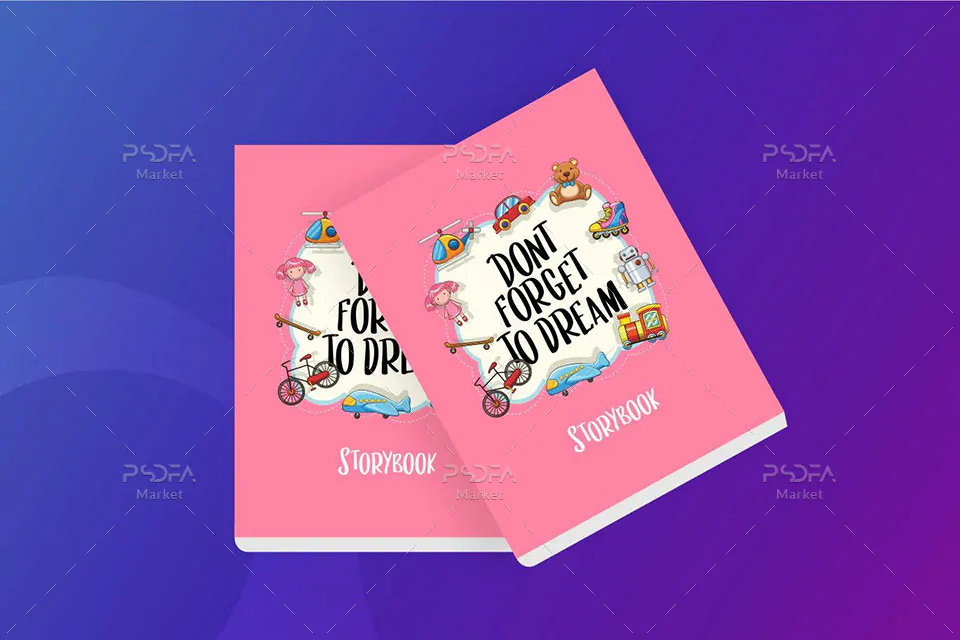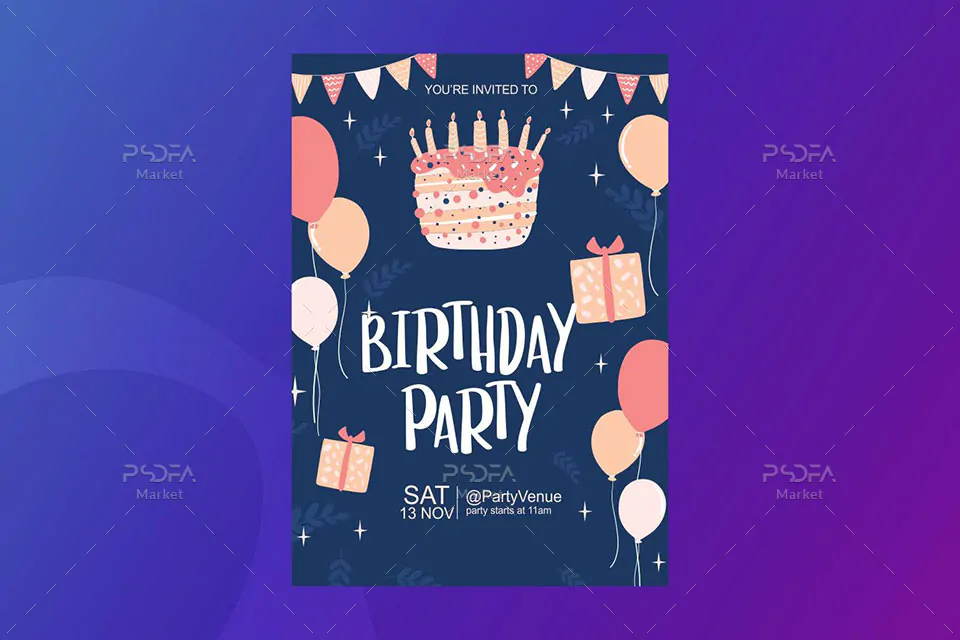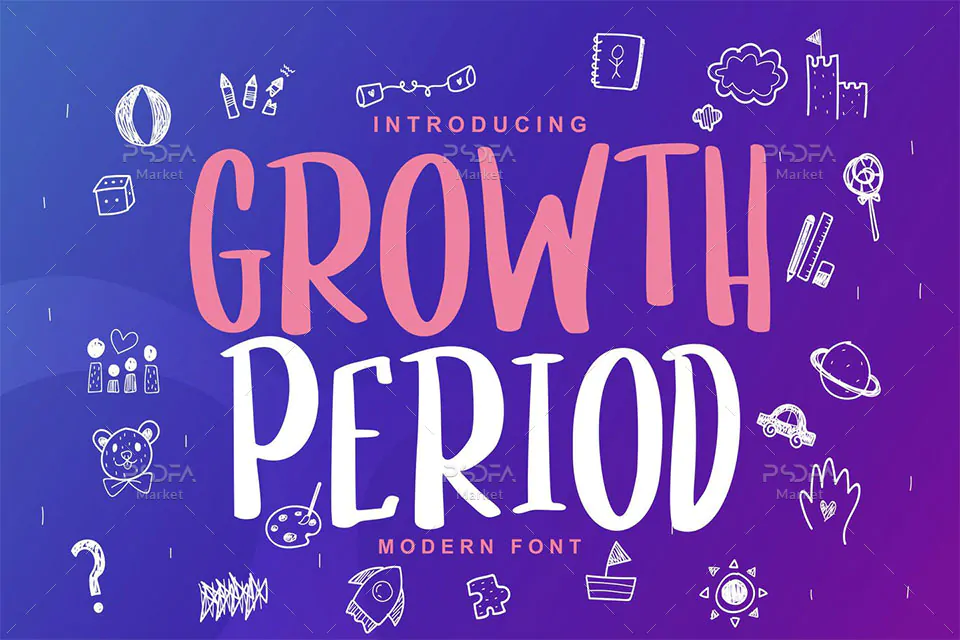
فونت مدرن کودکانه و کارتونی Growth Period یک قلم فوق العاده زیبای انگلیسی است که مناسب جهت استفاده در طرح و پروژههای گرافیکی مختلف به خصوص طراحی انواع تصاویر کودکانه و کارتونی میباشد. این فونت زیبا در قالب 2 فایل OTF, TTF در فایل محصول قرار دارد که با نصب یکی از این 2 فرمت در پوشه فونتهای سیستم میتوانید از این فونت انگلیسی در تمام نرم افزارهای گرافیکی و تایپ متون همچون فتوشاپ، افتر افکت، پریمیر، ورد، پاورپوینت و … استفاده کنید.
فونت Growth Period در وزن معمولی (Regular) طراحی شده است که میتوانید از آن در طراحی بسته بندی محصولات، لوازم التحریر، بگهای خرید و هدیه، ظروف یکبار مصرف، رابط گرافیکی گیم، تقویم، پوستر، بنر، بروشور، تراکت، طراحی صفحات وب و دیگر طرحهای گرافیکی استفاده کنید.